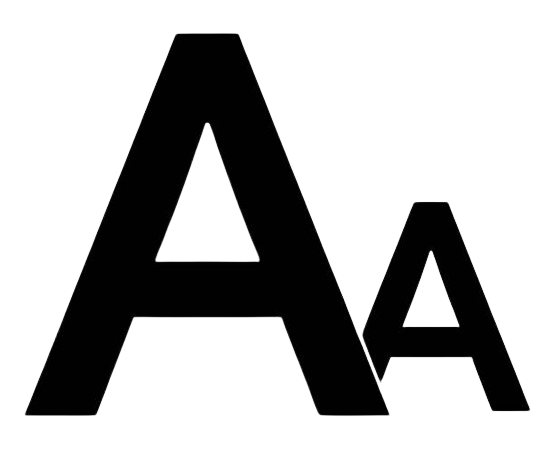
Apa Itu Font Size
Apa Itu Font Size – Font size adalah parameter kritis dalam desain tipografi yang menentukan ukuran huruf dalam dokumen atau desain grafis. Ukuran huruf ini diukur dalam poin, dengan satu poin setara dengan 1/72 inci. Dalam konteks tipografi, pemilihan font size memiliki dampak besar terhadap keterbacaan, hierarki informasi, dan tampilan keseluruhan suatu teks. Dengan mengatur font size yang sesuai dapat membuat dokumen kita menjadi lebih rapih dan akan mudah dibaca
Mengatur Font Size Supaya Dokumen Rapih
Ukuran huruf yang tepat adalah kunci untuk menciptakan tampilan teks yang seimbang dan mudah dibaca. Font size yang terlalu kecil dapat menyulitkan pembaca dan mengakibatkan kelelahan mata, sementara font size yang terlalu besar dapat menghabiskan ruang desain dan memberikan kesan kurang profesional. Pada umumnya, ukuran huruf untuk teks tubuh dalam dokumen teks biasa berkisar antara 10 hingga 12 poin, tetapi ini dapat bervariasi tergantung pada preferensi desainer dan kebutuhan proyek.
Pemilihan font size juga dapat digunakan untuk menekankan hierarki informasi. Misalnya, judul atau heading biasanya memiliki ukuran huruf yang lebih besar daripada teks badan untuk menonjolkan pentingnya informasi tersebut. Dengan menggunakan variasi ukuran huruf, desainer dapat membimbing pembaca melalui hierarki informasi dan membuat desain lebih terstruktur.
Penting untuk dicatat bahwa ukuran huruf bukan hanya tentang angka mutlak, tetapi juga harus dipertimbangkan dalam konteks desain keseluruhan. Dalam beberapa kasus, desainer mungkin perlu menyesuaikan ukuran huruf agar sesuai dengan konsep estetika dan kebutuhan visual spesifik proyek. Penggunaan font size yang konsisten juga membantu menciptakan tampilan yang bersih dan terorganisir.
Dalam dunia digital, pengaturan font size menjadi lebih dinamis karena tampilan dapat bervariasi tergantung pada perangkat dan layar yang digunakan. Responsif terhadap perangkat dan resolusi layar adalah pertimbangan tambahan yang perlu dipikirkan oleh desainer dalam menentukan ukuran huruf agar tetap optimal di berbagai platform.
Dengan memahami dan menggunakan font size dengan bijak, desainer dapat mencapai keseimbangan yang tepat antara estetika dan keterbacaan, menciptakan pengalaman visual yang memadai untuk pembaca atau pemirsa target. semoga penjelasan mengenai apa itu font size ini dapat membantu kita lebih mahir dalam membuat dokumen, memang terkadang hal tersebut terkesan remeh tetapi dapat berdampak besar dalam dokumen yang kita buat. sekian